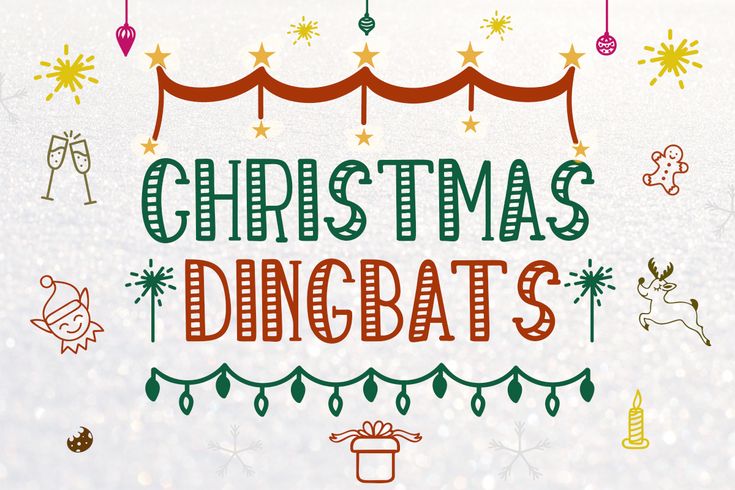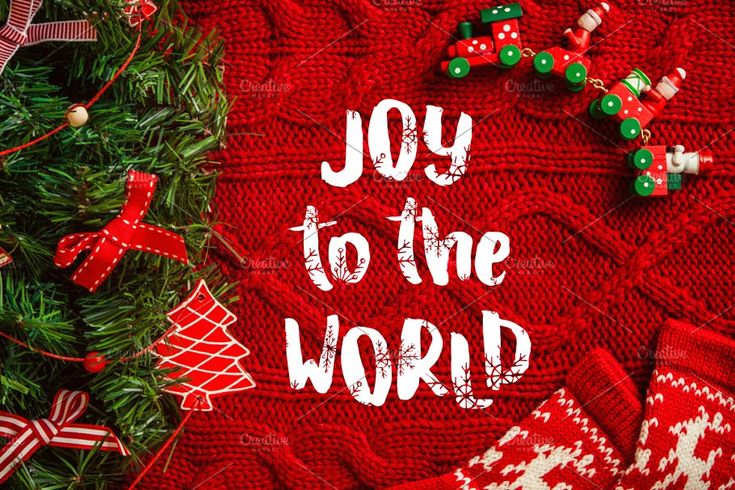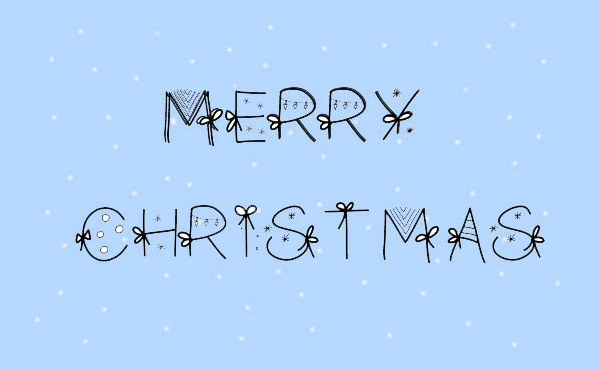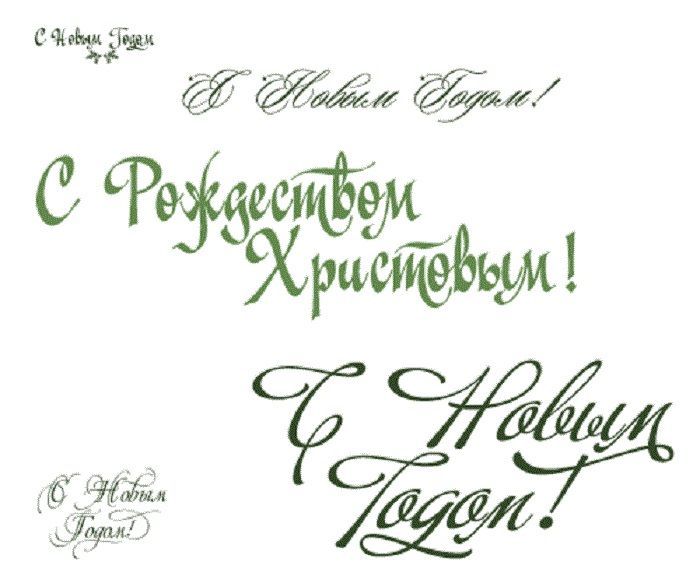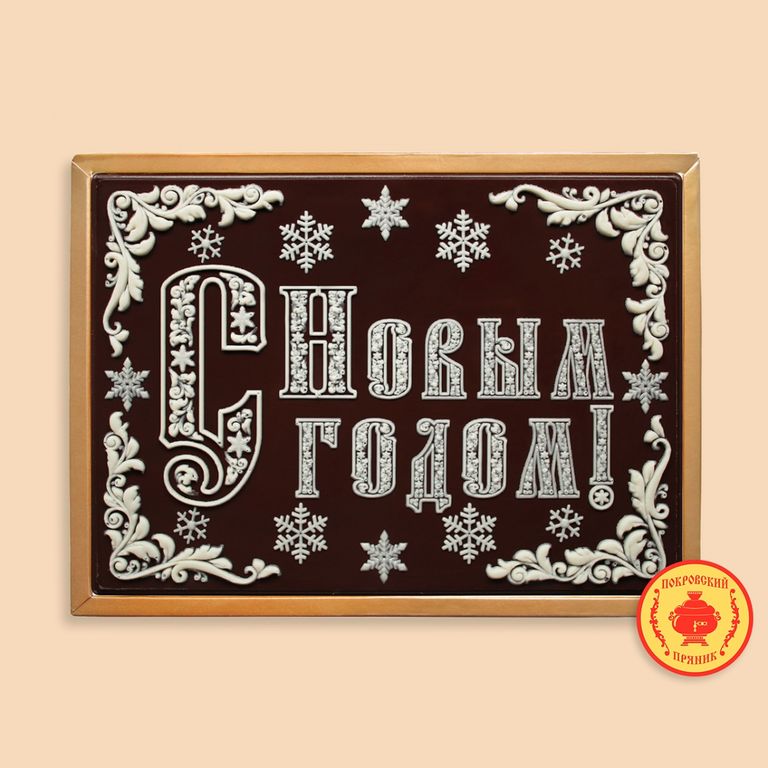
ruДизайнеры Brand Hub оценивают Сант, оленей, праздничные иконки и новогоднюю пальму от Вкусвилла. Стрём или норм — голосуйте в статье.
Мы узнали у лучших дизайнеров нашей платформы, что их бесит в новогоднем брендинге, а что нравится. Предлагаем вам дать свои оценки и узнать, совпадаете ли вы во мнении с дизайнерами Brand Hub.
Начнем со стрёма, а в конце покажем норм — хотим, чтобы и года, и статьи хорошо заканчивалось. С наступающими праздниками вас!
Стрём
- Штампы: Санта, ёлки и олени
- Брендированные календари
- Фон из снежинок
- Новогодний шрифт с завитушками
- Заезженные цвета
Норм
- Праздничные иконки приложений
- Необычная адаптация логотипов
- Новогодние символы по-новому
- Атмосферная упакова
- Геймификация
Стрём
Штампы: Санта, ёлки и олени
Санты, Деды Морозы, ёлки, гирлянды, олени, леденцы, снеговики, перевязанные красной лентой коробки с подарками — это всем надоело ещё 10 лет назад.
Классические атрибуты праздников не раздражают, если это часть легенды бренда, его айдентики. Но если вы не занимаетесь брендингом Coca-Cola — порадовать аудиторию штампами не получится.
Брендированные календари
Типичный новогодний мерч брендов — настенные календари. Их вообще до сих пор кто-нибудь вешает?
Фон из снежинок
От директора приходит задача — нужен новогодний фон для постов в соцсетях.
— Зачем нужен? — Ну, нужен и всё. Вася, ты дурак что ли? — Окей, нафигачим снежинок!
Новогодний шрифт с завитушками
Совещание топ-менеджмента:
— Нужно поздравить всех с Новым годом!
— Клиентам совершенно необходимо 100500-е поздравление.
— Нельзя просто написать «Поздравляем!». Давайте шрифт новогодний сделаем — будет по-праздничному.
Так рождаются затасканные шрифтовые клише. Занавес.
Иногда компаниям кажется, что в декабре все цвета, кроме красного, зелёного и белого, исчезают.
А они есть, как тот самый суслик!
Норм
Праздничные иконки приложений
Хочешь тыкнуть на приложение, а там — милая новогодняя иконка. Пользователю на душе тепло и приятно, как будто бренд его пледом укрыл и по беспокойной голове погладил.
Необычная адаптация логотипов
Сразу оговоримся: нацепить на логотип новогодний колпак — это не «необычная» адаптация. А вот варианты новогодних лого Mastercard и Heineken — огонь!
Новогодние символы по-новому
Некоторые бренды показывают атрибуты Нового года так, что взгляд сам цепляется за картинку. Например, праздничная «ёлочка» от Вкусвилла. Обычную ёлку пользователь пролистает и даже не вспомнит, а вот ёлко-пальму!